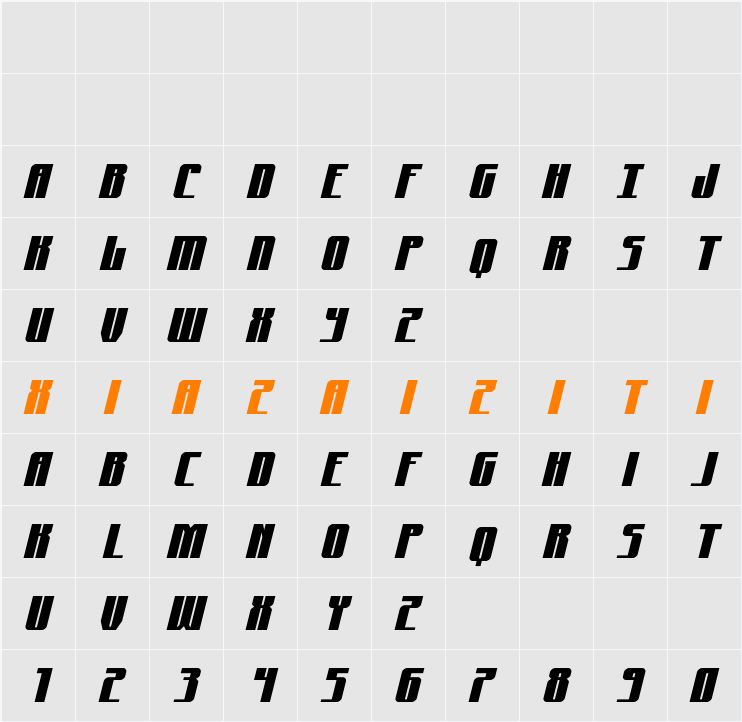
Xeno-Seeker Spaced Italic
Xeno-Seeker Spaced Italic,这款字体结构工整、笔画清晰,兼顾美观与易读性,适用于标题、正文、海报、包装、LOGO 等多种场景。字形优雅稳定,风格百搭耐看,适配日常排版与创意设计,让文字呈现更舒适、更具质感。Xeno-Seeker Spaced Italic一笔一画,皆是细节,以均衡的比例、流畅的线条打造舒适视觉体验,字形端正大气,风格简约现代。无论是商业设计、品牌宣传还是日常排版,都能轻松驾驭,让文字更有格调与力量。Xeno-Seeker Spaced Italic字体下载。